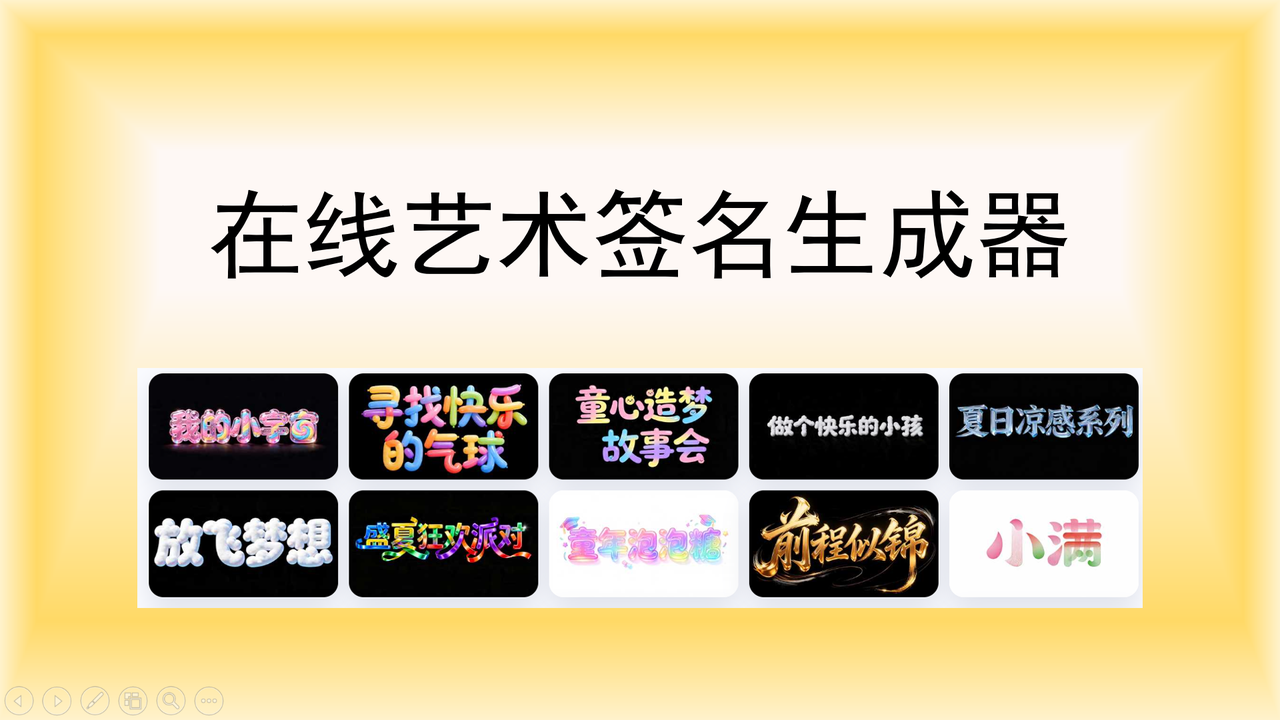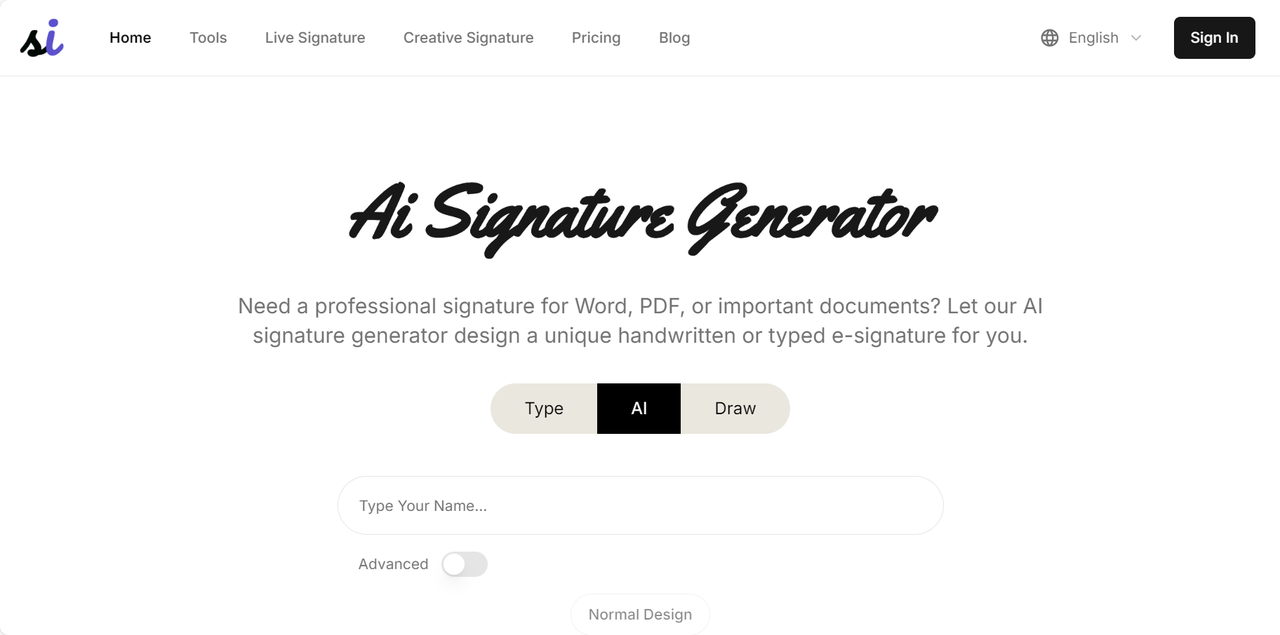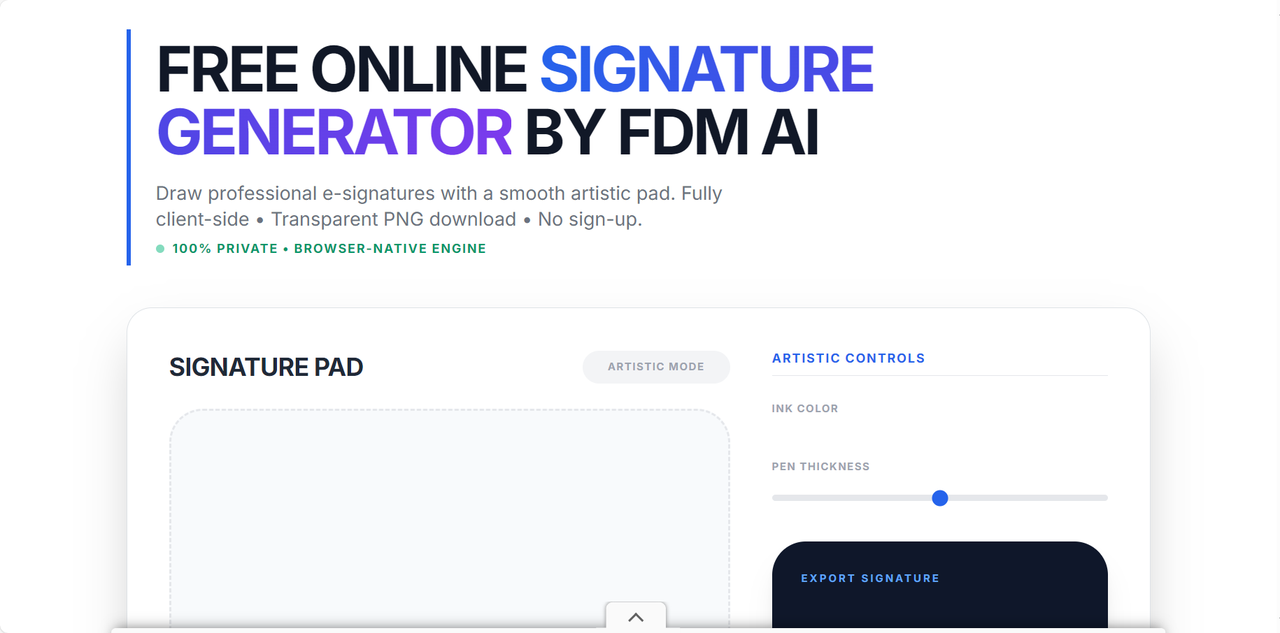
不用手写!在线艺术签名生成器,明星同款签名设计免费版
每次看到明星艺人或是商务人士的签名都很羡慕?想要拥有像他们那样气场十足、潇洒流畅的手写签名,但自己写字又不够漂亮?不用再为此困扰啦!今天给大家精心整理了 4 款在线艺术签名生成器,无需任何设计基础,不用自己手写,轻松搞定各种风格的签名设计。这些工具堪称是明星同款签名设计的免费版,从 AI 智能生成到真实模拟手绘效果,超多功能等你来探索,满足日常签名的需求,又能拥有一个兼具专业感和高级感的艺术签名。选择一个最适合你的在线艺术签名生成器,再也不用羡慕别人笔下的字迹了!
一、字由
字由是国内设计师最常用的字体管理工具,但它内置的 AI 字体功能其实是一个极其强大的在线艺术签名生成器。操作流程非常简单,进入字由官网首页,在顶部导航栏中点击【AI 工具】-【AI 字体】,你会看到大量精心设计过的字体模板。在分类筛选区域选择“艺术签名”或是“手写体”,搜索出来的字体模板都非常适合用于签名设计,清晰有力还是行云流水的签名,各种风格应有尽有。选择一个喜欢的模板,点击“做同款”,在右侧的文本框输入你的名字,点击“立即生成”,等待 20 秒钟左右,一张设计感十足的艺术签名图片就生成了。整个过程完全不需要手动书写,字由会帮你搞定一切,连墨迹变化、笔画过渡都会经过智能优化,最终呈现出一个和样图效果一致的自然风艺术签名。生成后的艺术签名可以直接下载为透明背景的 PNG 图片,直接拖入其他设计软件、Word 合同、PDF 文件、简历封面或邮件签名档中使用。收费方面也非常友好,每日登录赠送免费算力,日常零散的设计需求基本不用花钱。
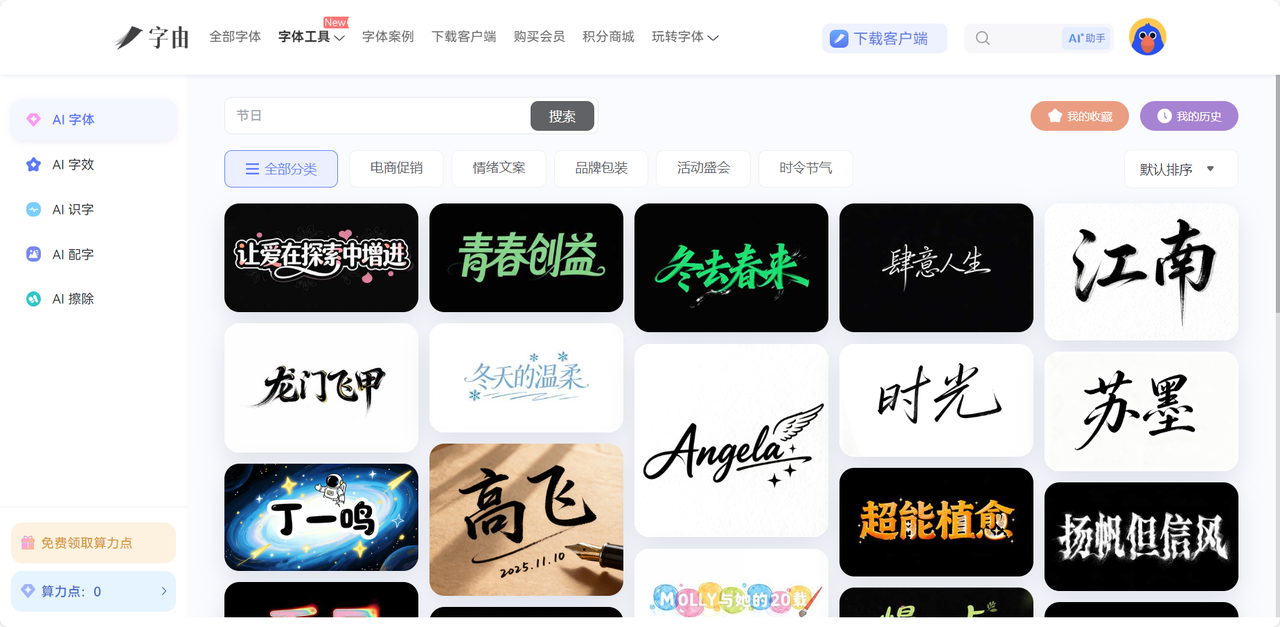
二、Signature Sketch
Signature Sketch 是一个在浏览器本地运行的开源艺术签名生成器,最大的亮点就是保护你的隐私安全。所有的签名绘制和生成过程全部在你的浏览器内存中完成,你输入的任何文字内容都不会被传输到外部服务器,刷新页面后会自动清除数据,特别适合在商务合同、法律文件等正规且需要隐私权的场景中使用。而且它完全免费、无需注册、无需登录、不用下载软件,只要点开网页就可以在线生成签名。
目前为止,Signature Sketch 提供了两种生成艺术签名的方式。第一种是手绘模式,如果你是想要保留自己的书写特色且你有一定的书法功底,这个模式非常适合你。用户直接用鼠标、手指或者触控板在画板上直接书写,Signature Sketch 内置的按压感应系统会根据你的书写速度产生自然的笔画粗细过渡,也会在一定程度上美化你的字体,最终形成一个完整的艺术签名。第二种方式是自动生成模式,这就是完全的傻瓜式操作了,不讲究书法技巧。你只需要在文本框内输入自己的姓名,Signature Sketch 会自动生成多种手写体风格的签名供你挑选,其实肉眼看下来,这些签名同样笔画流畅、结构协调,很像是专业书法大家帮你设计好的作品。和字由一样,生成后的签名可以直接导出为透明背景的 PNG 图片,后续使用起来会很方便。
三、FDM AI Online Signature Generator
对于想要追求真实手写感和专业视觉效果的小伙伴们来说,FDM AI Online Signature Generator 绝对是一款非常好用的工具。它的签名生成功能是采用了高敏感度的按压感响应模式,当你用鼠标或触控笔书写的时候,系统会实时捕捉你的力度,从而模拟出真实的手写墨迹感。比如下笔较轻的时候,形成的笔画线条很淡,下笔过重的时候,形成的线条会更粗且颜色更深。这一点也是我认为 FDM AI Online Signature Generator 最大的优势,在同类型的其他工具中其实很少见到可以如此还原真实笔墨效果的字体。和 Signature Sketch 一样,这款艺术签名生成器也秉承着隐私保护的原则,你输入的签名数据不会泄露传输到其他服务器,保障你的签名安全。
除此之外,我还发现 FDM AI Online Signature Generator 有一个很好用的功能,就是它支持跨设备统一输入。无论你用电脑鼠标还是触控板,或者是在手机平板上使用触控笔书写性命,它都可以保证输入笔画的稳定性和一致性,不会出现锯齿状的抖动,线条非常流畅自然。用它来生成艺术签名全程只需要两分钟,从绘制到下载都可以全部搞定。觉得自己字不好看的小伙伴就别用这个了,去选择上面那些可以一键 AI 生成的工具哈。
四、Refont AI
Refont AI 是一个基于人工智能的在线字体生成工具,主打 AI 书法生成、个性签名生成、手写复刻等功能,无需掌握任何设计技巧,几秒钟生成专业的签名效果。它的操作过程可以用“输入、点击、出图”三步来形容:首先打开官网进入 AI 签名生成器页面,输入你的姓名(支持中文或英文);其次点击“生成”按钮;最后 Refont AI 会基于你的名字分析生成多个风格各异的艺术签名方案。我真的会强烈夸赞它的字体风格,极其丰富,例如古朴庄重的隶书、洒脱奔放的草书或者是商务简约的黑体、精致张扬的花字等等,想要的风格应有尽有,连笔过渡自然、墨迹变化恰到好处。生成艺术签名后还支持为文字添加背景纸效果(普通白纸、横线作业纸、方格纸等等),可以导出的签名效果会自带纹理感,视觉上看起来更加自然。最关键的是,Refont AI 还拥有书法 Logo 生成器的功能,只需要输入品牌名称,就可以帮助你快速生成一个国风设计感的品牌 Logo。如果你最近 有在做一些国潮相关的品牌设计,不妨来体验一下 Refont AI 吧,感受不同书法流派的艺术魅力,生成精致美观且有文化底蕴的字体。
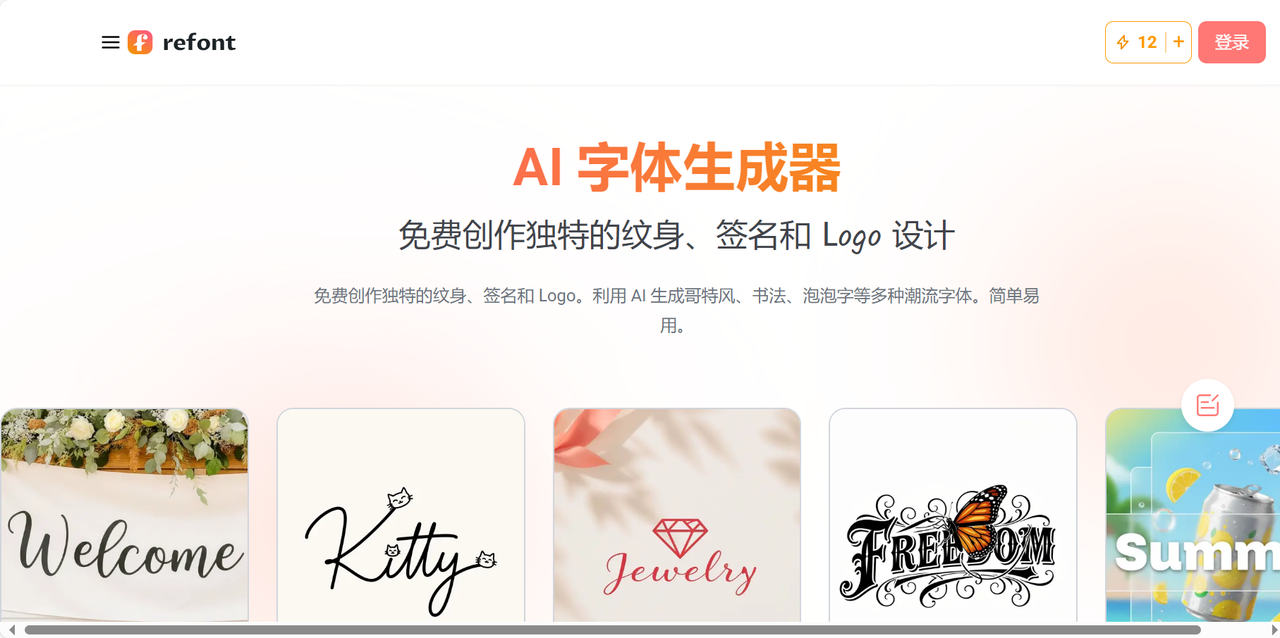
关于在线艺术签名生成器的介绍就在这里告一段落,有没有哪款工具是你心仪的呢?其实这些工具都可以满足不用书写、不用掌握设计技能、在线一键生成艺术签名的需求。注重隐私体验就选择 Signature Sketch;想直接用 AI 一键生成就选择字由、Refont AI;如果想要自己手绘,那么 FDM AI 是最好的选择。有了这些工具的帮助,下次想要电子艺术签名的时候,直接打开一款工具,快速获得明星同款签名设计!